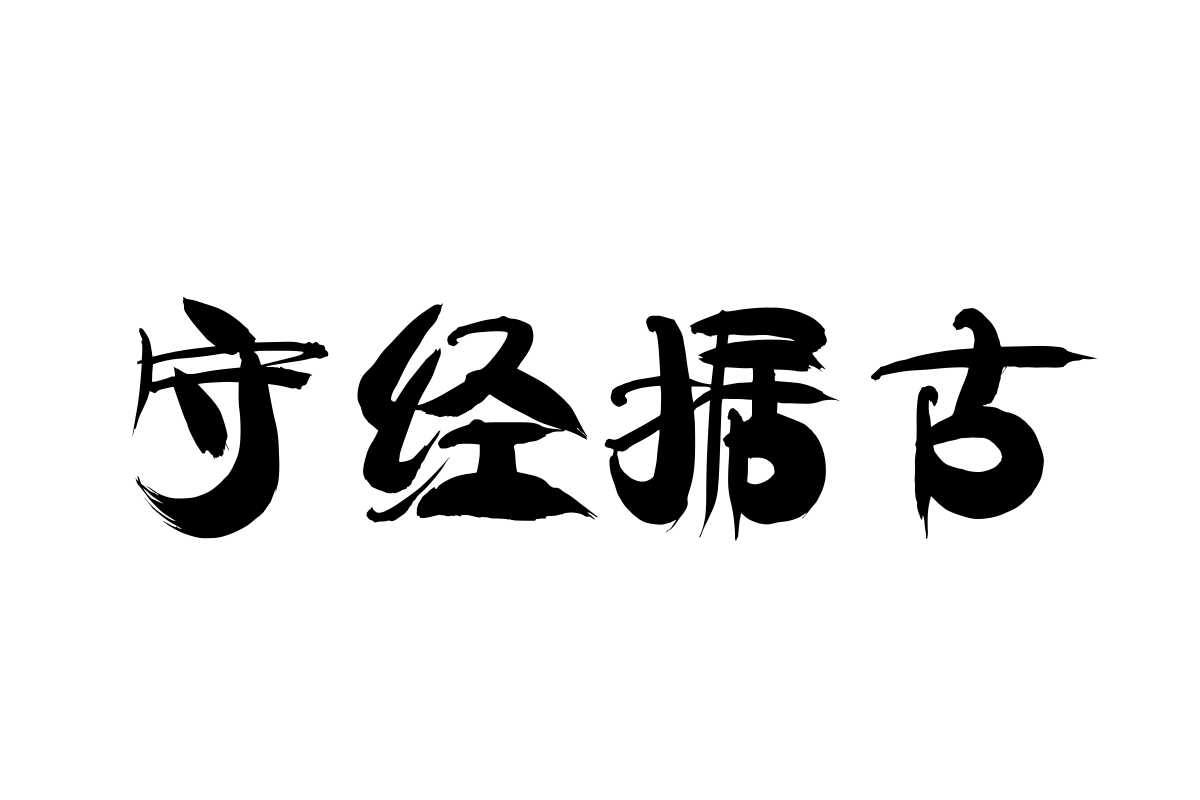
汉仪迪升山涧体是一款具有独特风格的中文字体,由汉仪字库设计。这款字体采用了传统的书法风格,笔画流畅自然,字形优美大方。它的特点是笔画粗细适中,结构紧凑而不拥挤,给人一种古朴典雅的感觉。
汉仪迪升山涧体的字体特点是:笔画粗细适中,结构紧凑而不拥挤,给人一种古朴典雅的感觉。它的字形优美大方,适合用于各种需要展示传统文化和艺术美感的场合。